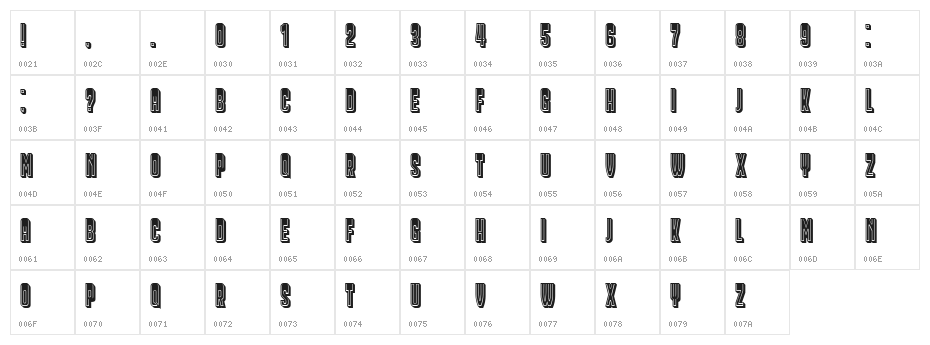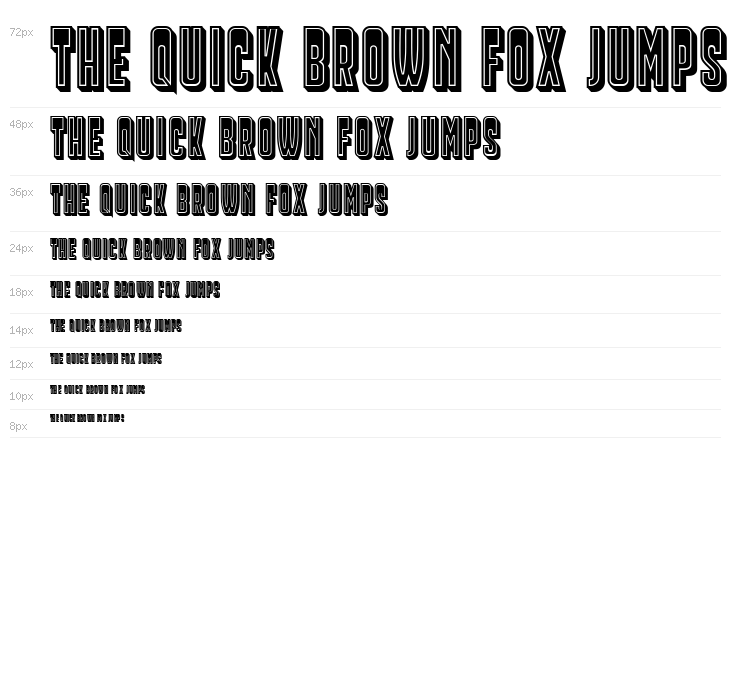
Businessman Regular Font
| Vorgeschlagene Projekte | This font is perfect for branding projects, posters, and signage where a strong, authoritative presence is needed. It can also be used in editorial design for magazine covers or feature articles. |